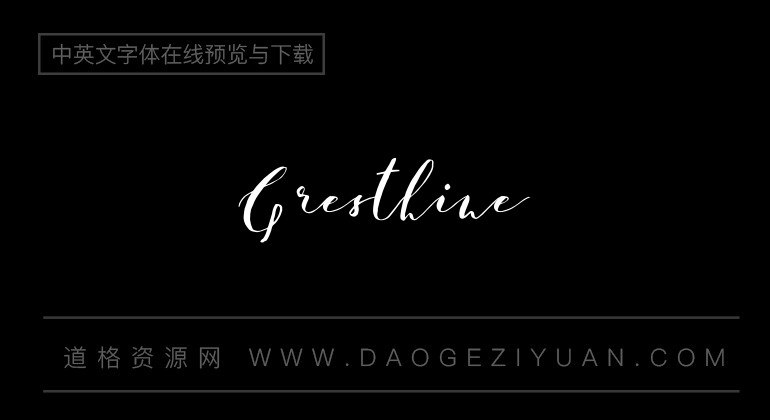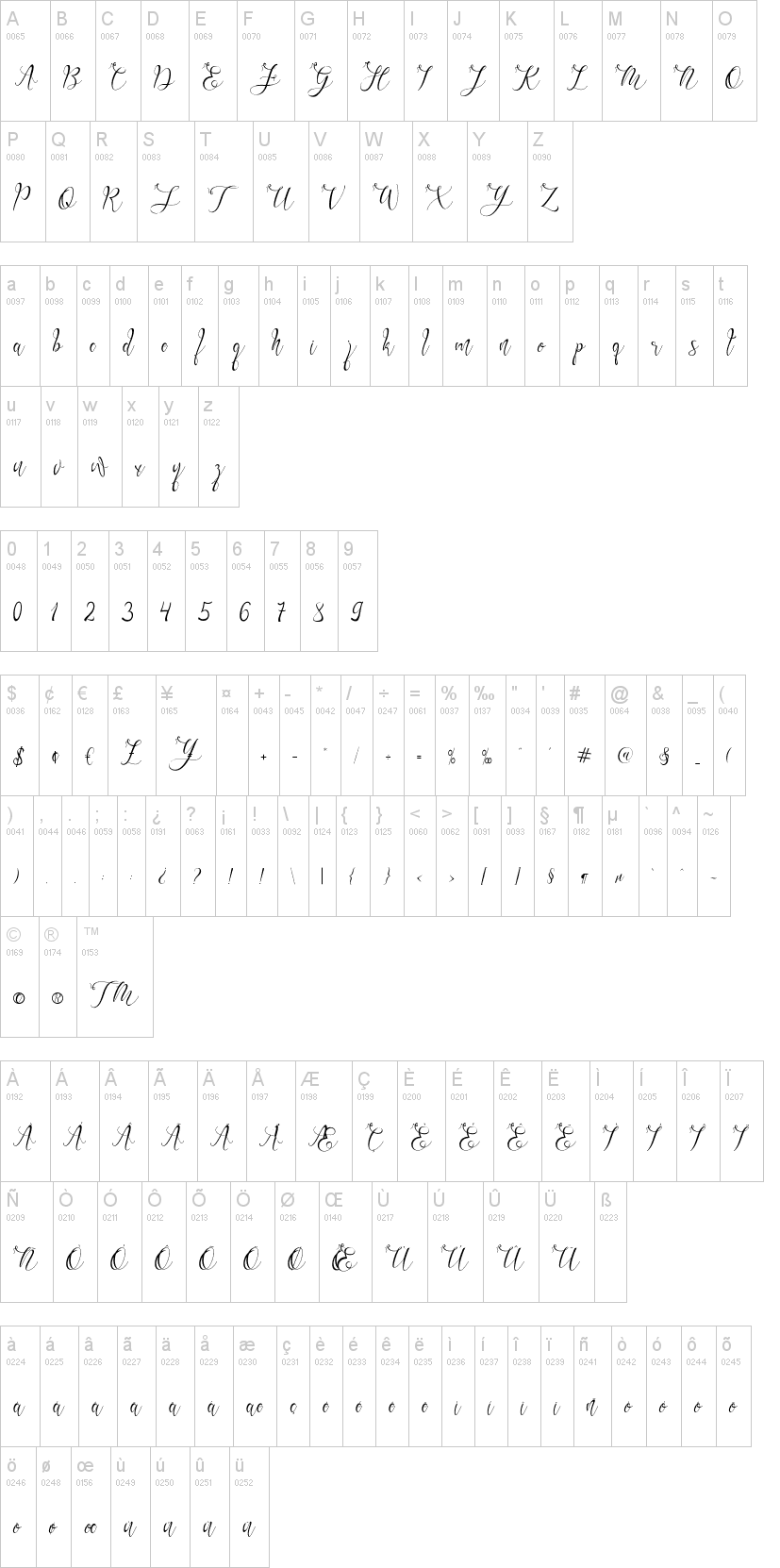
Gresthine 字体是一种源自英国的手写字体,由英国设计师Gresthine创作。Gresthine字体具有细腻的线条,柔和的曲线,它的字形更加细腻,温柔,优雅,它更加符合现代设计的风格,适合用于小型的文本,也可以用于大型的标题,更适合现代设计风格。内容介绍
Gresthine是一款非常不错的手写艺术字体,具有很好的视觉感,适合于文化类的宣传设计、商业类品牌的广告和产品包装设计以及个性化文字排版等较多场景。